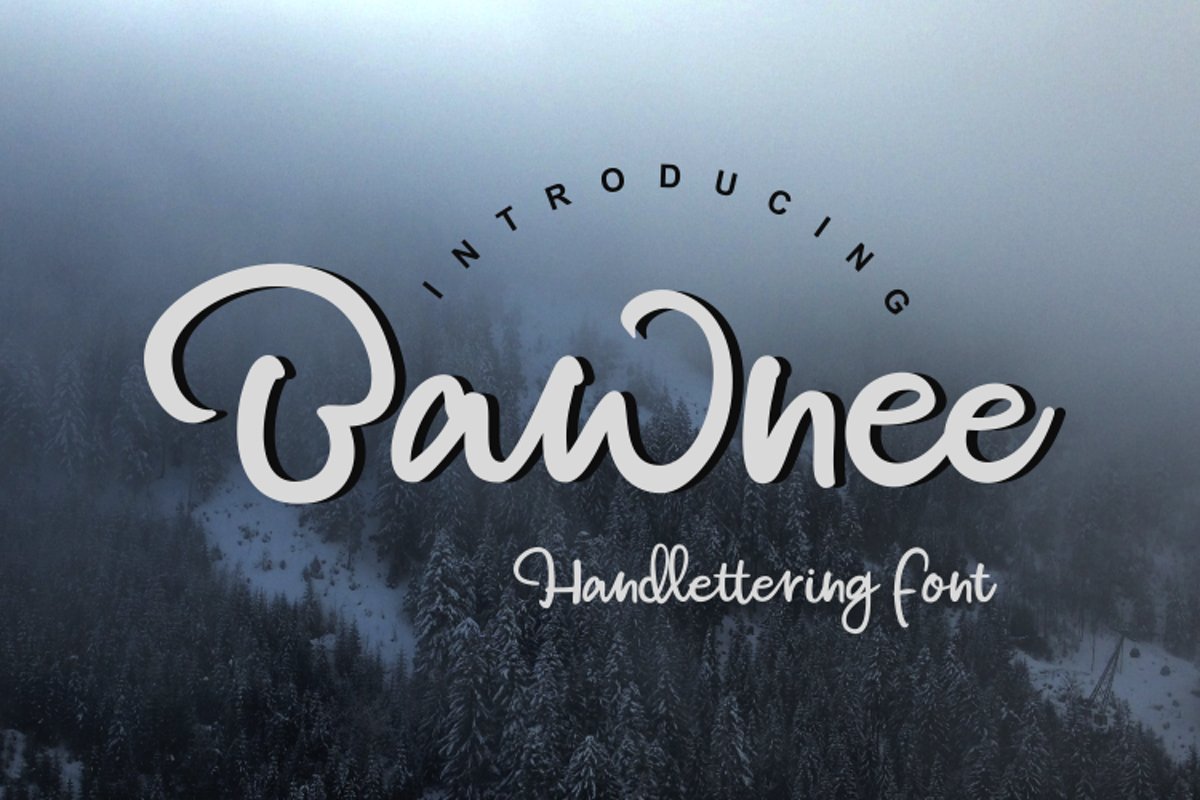
bawnee - handlattering font
bawnee
Halo semua kami ingin memperkenalkan produk baru dari toko kami.
kami beri nama "Bawnee"
font tulisan tangan dengan gaya alami yang terinspirasi oleh gaya tulisan tangan modern.
Font ini sangat cocok untuk tanda tangan, logo dan banyak proyek yang sedang mengerjakannya hari ini.